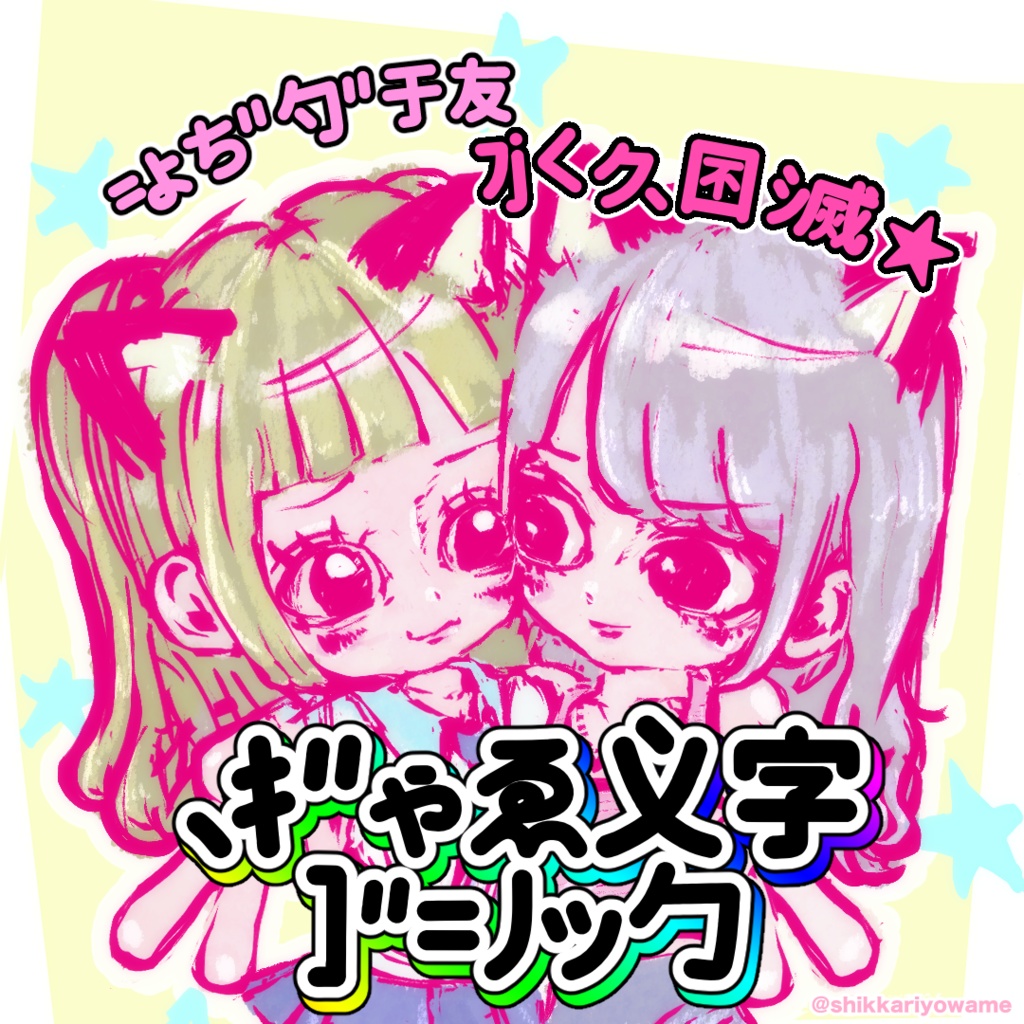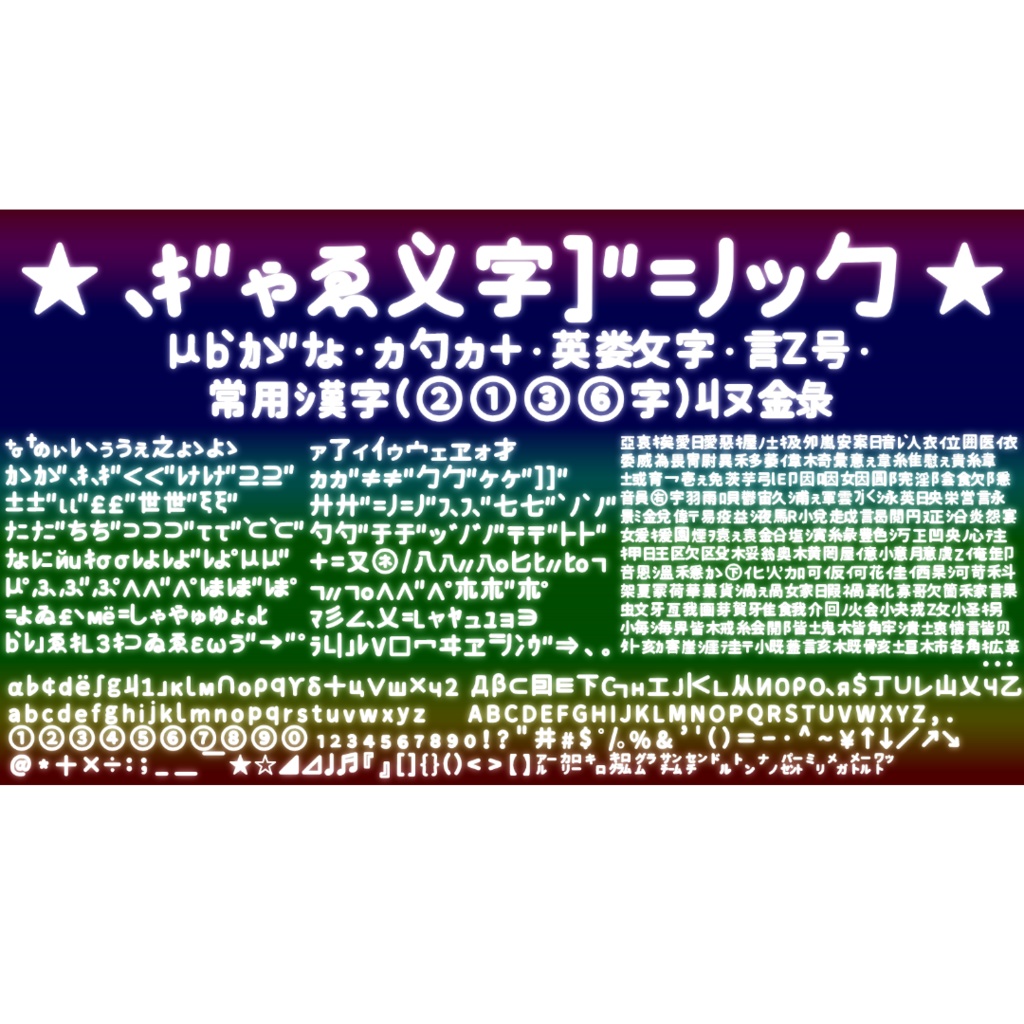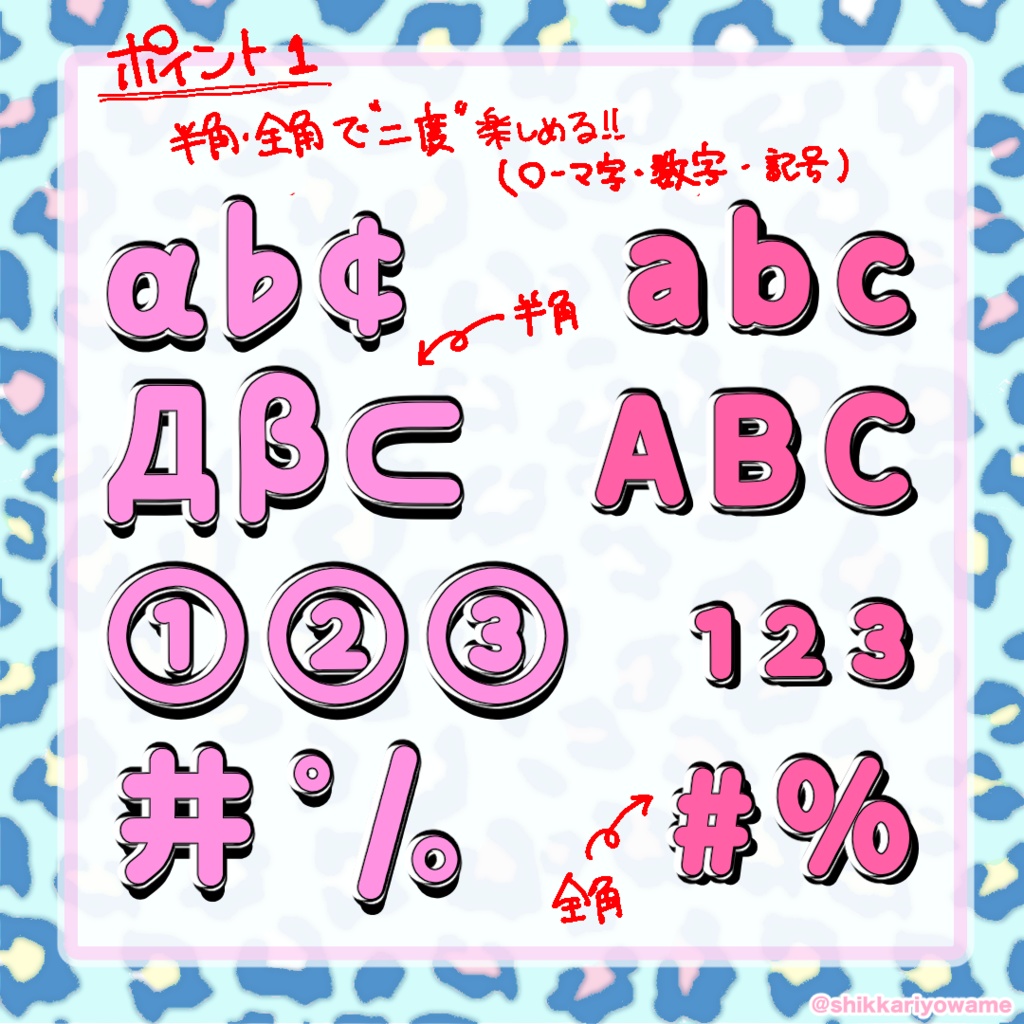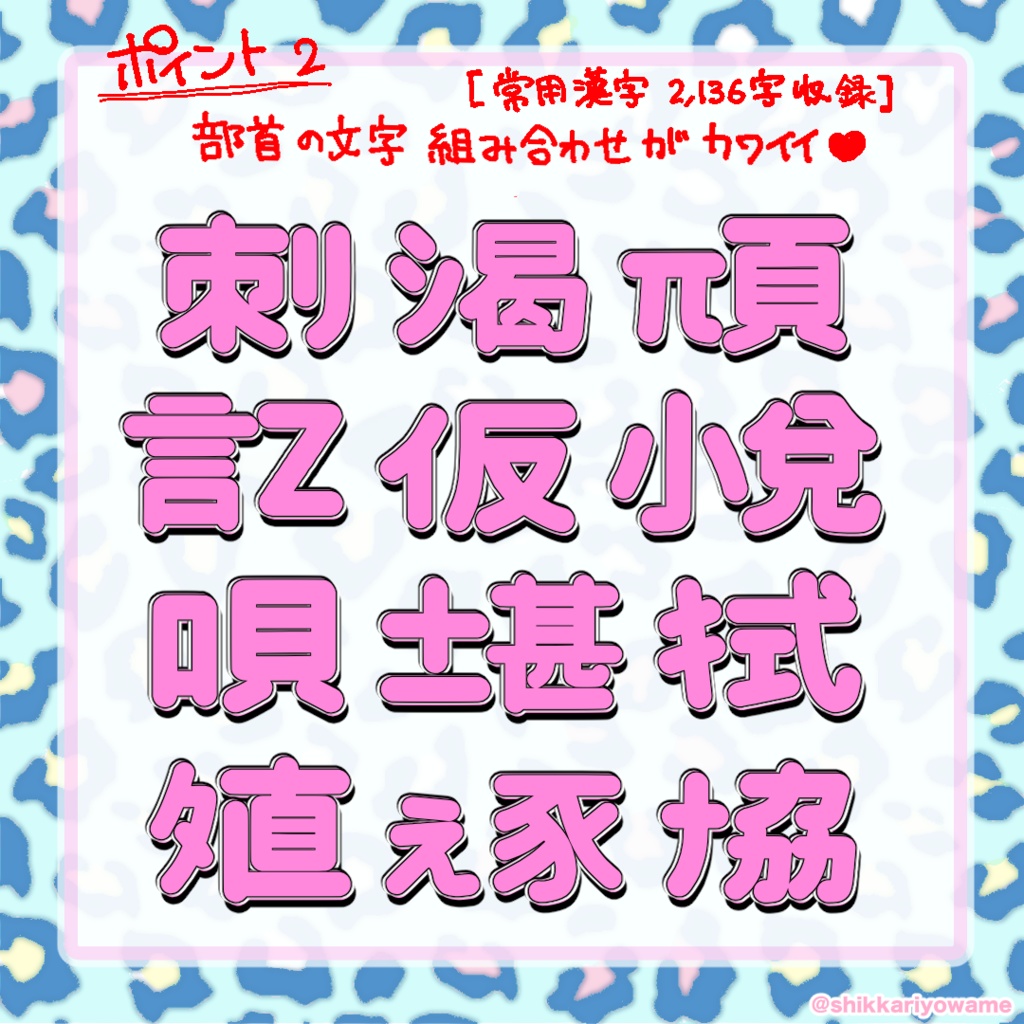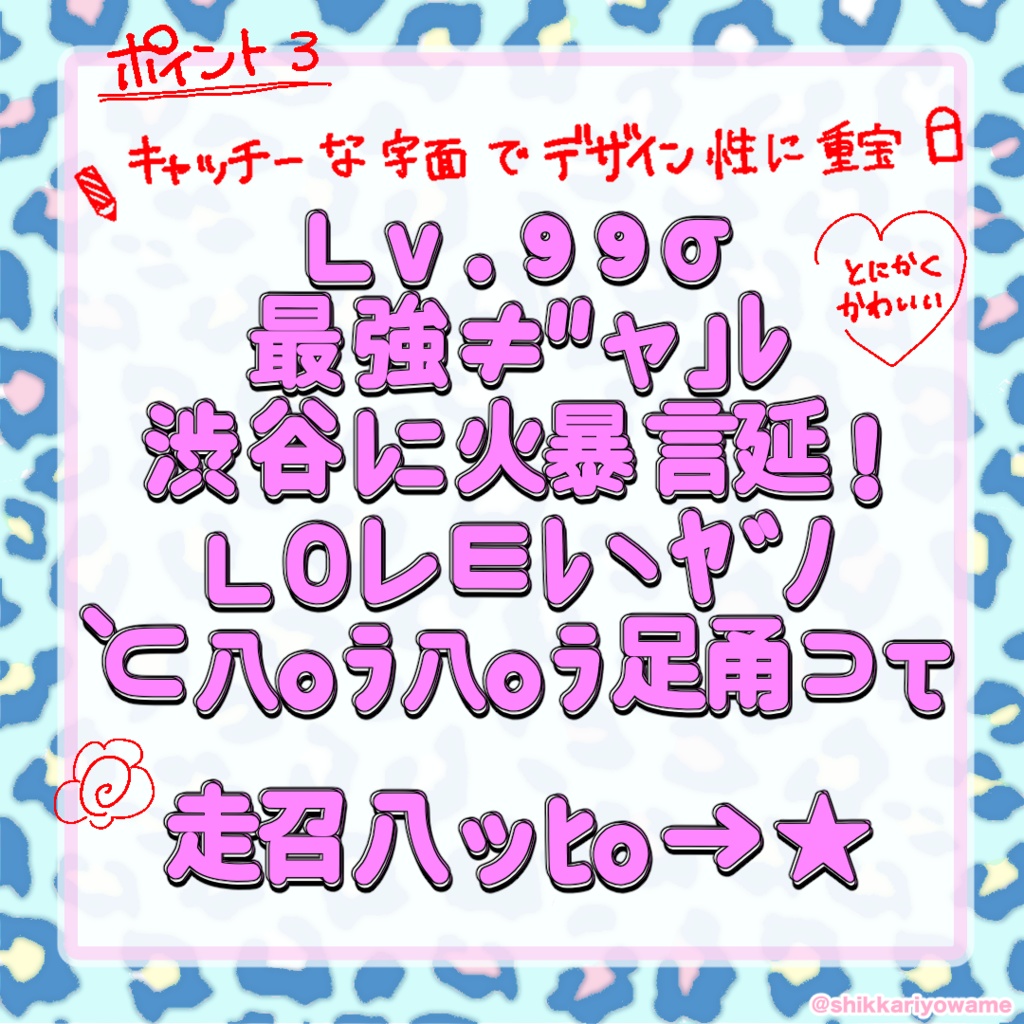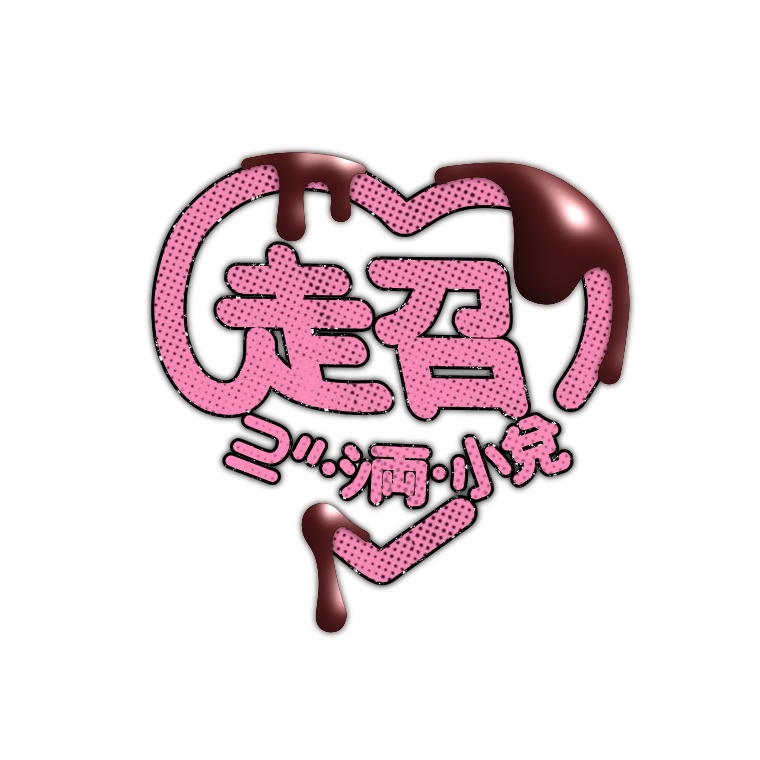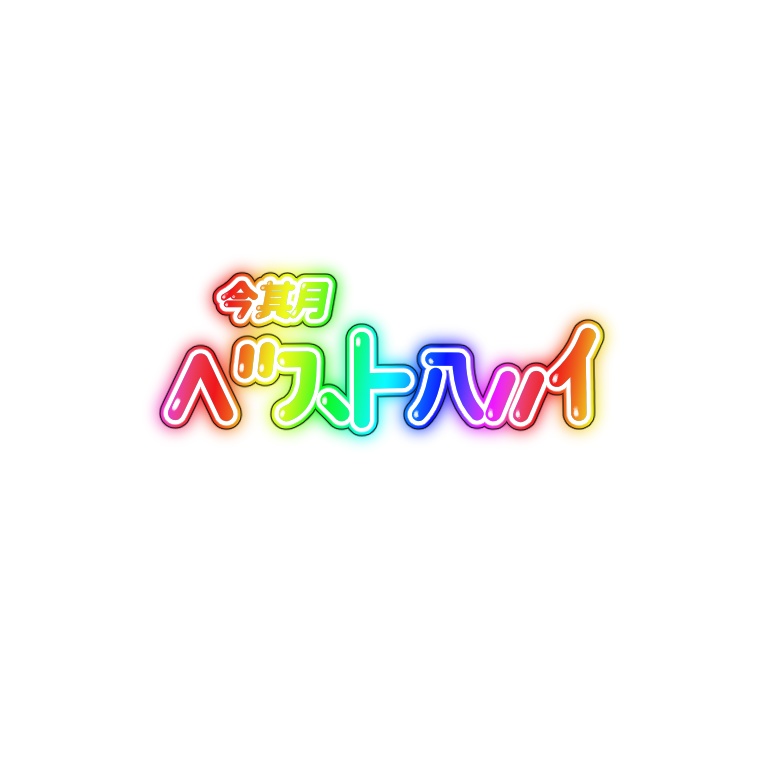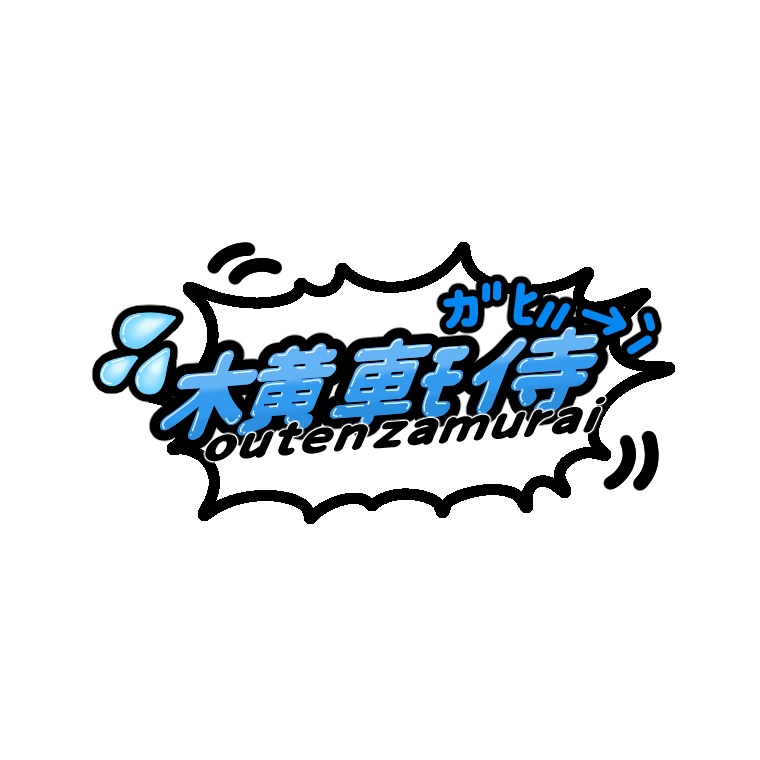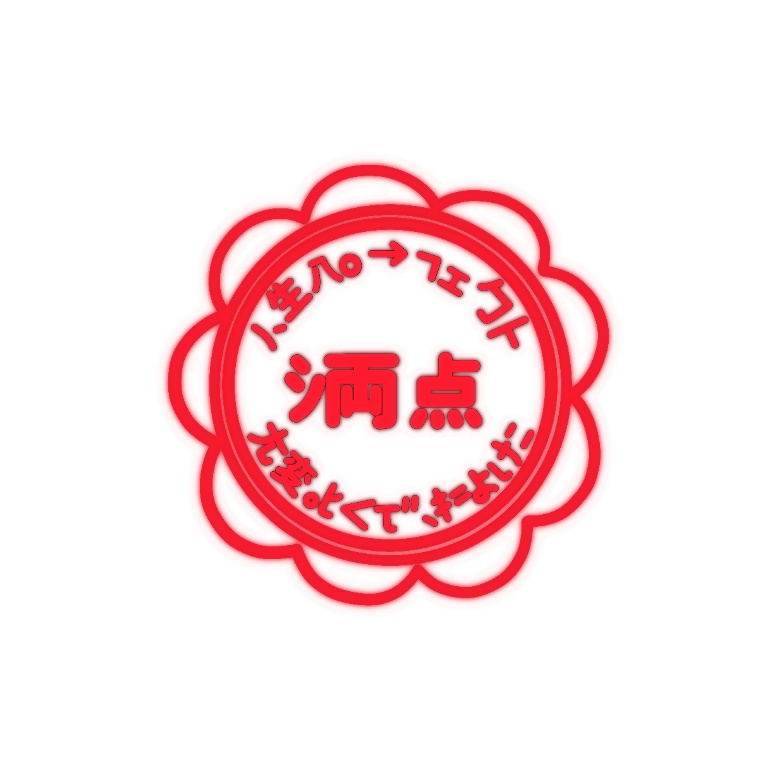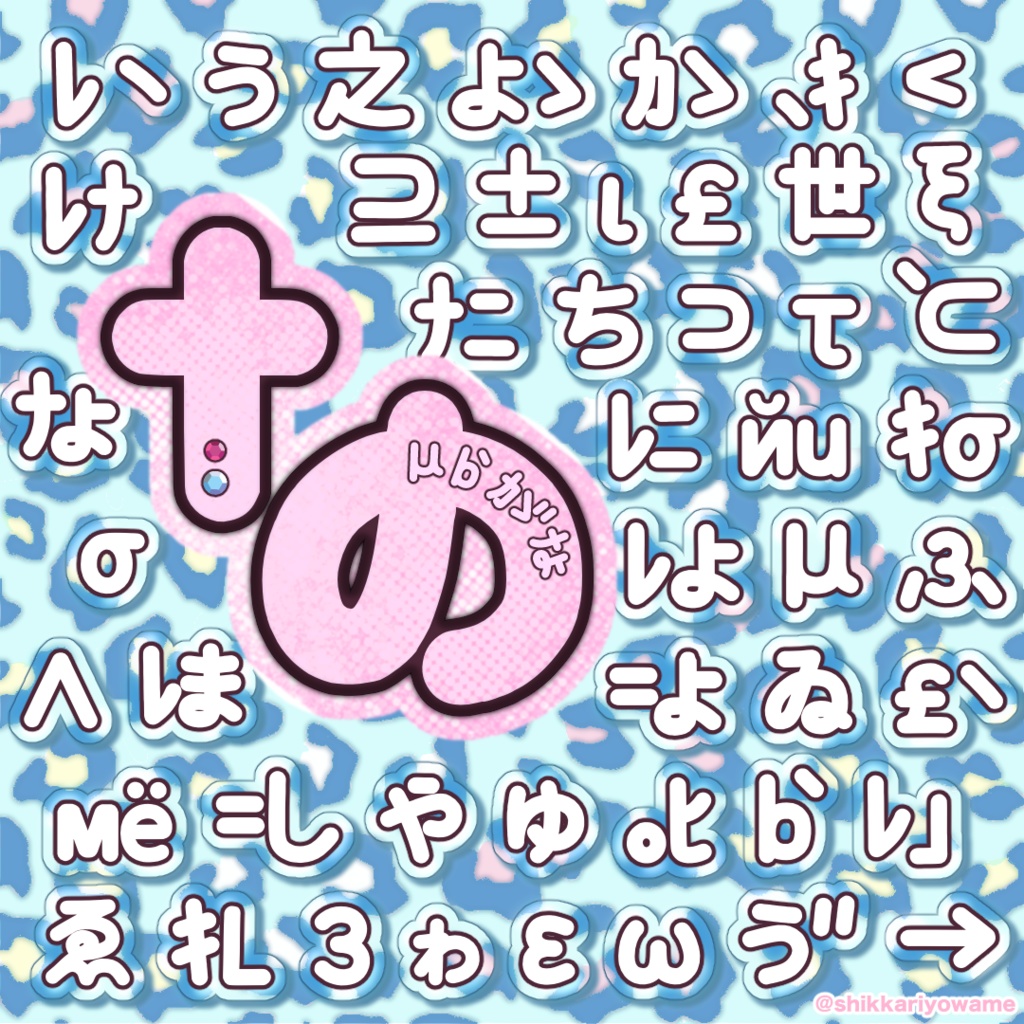
ぎゃる文字ゴシック【フリーフォント】
ぎゃる文字ゴシック Xアカウント( https://x.com/shikkariyowame2 )をフォローでどなたでもDL可 【概要】 平成期に流行ったガラケーでひらがなやカタカナ、漢字、記号を「分解」したり「置き換え」たりと組み替えて表現するギャル文字をデフォルメチックなゴシック体で平成レトロカルチャーをフォント化しました★ デザイン性の高さから画面映えに重宝! 本フォントは源ノ角ゴシックに処理を施し加工しました。 Adobe-Japan1-6準拠 SIL OPEN FONT LICENSE Version 1.1の規約に準じます。 【ライセンス】 SIL Open Font License 1.1の下で公開しており、ライセンスの範囲内でご自由にお使いいただけます。 ・商用利用、再配布、改変可 どなたでも無料でお使いいただけます。 ・再配布を行う場合は、必ず本ライセンス(OFL)に基づき継承する必要があります。 以下のURLからSIL Open Font License 1.1確認いただけます。 ライセンス原文 https://openfontlicense.org/ ライセンス日本語訳 https://licenses.opensource.jp/OFL-1.1/OFL-1.1.html 【収録内容】 ・利用規約 ・TTFフォント ・ひらがな、カタカナ、数字、記号、アルファベット(free版) ・ひらがな、カタカナ、数字、記号、アルファベット、常用漢字2136字(支援版)※漢字は一部収録できていないものアリ ・オリジナル背景素材(支援版) 【支援版について】 収録データはfree版と異なり、+漢字(常用漢字)verをご利用いただけます。 加えて本フォントのsampleで使用した自作素材をお付けしております。 こちらの支援金は制作活動や維持費に対する支援・寄付として受け取らせていただきます。 応援励みになります!! また本フォントの詳細はフォントファイルと一緒に規約テキストを同梱しておりますので、そちらからご確認お願いします。 (※ https://lit.link/shikkariyowameからもご確認いただけます)